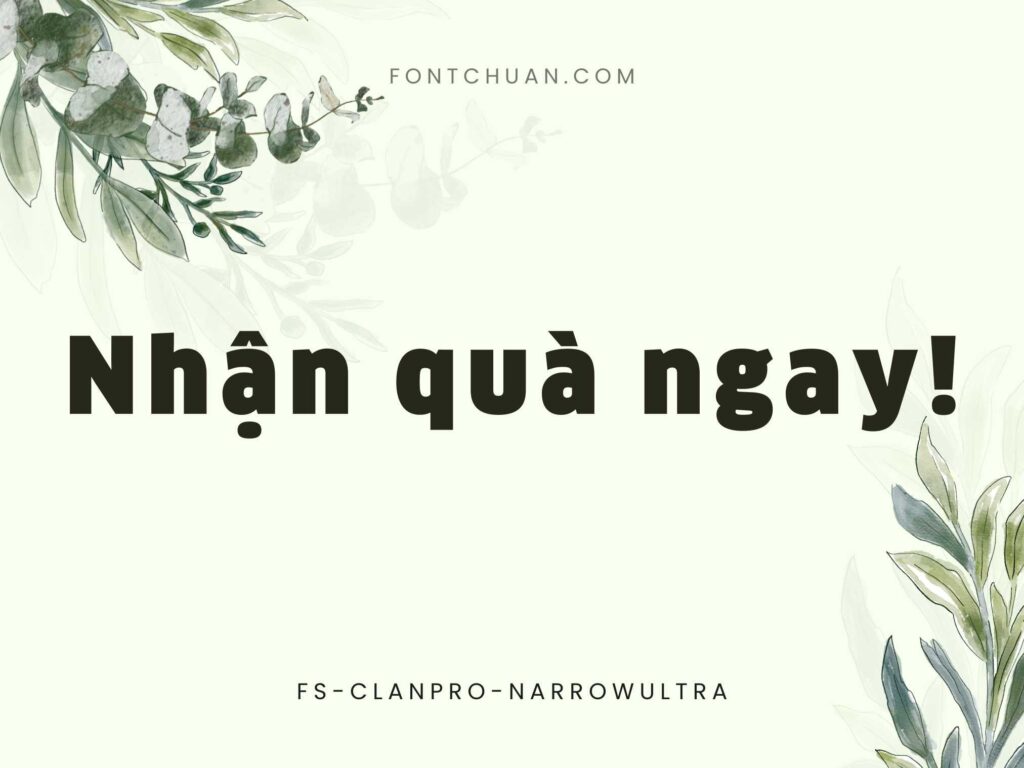
Font FS Clanpro-Narrowultra Việt Hóa
Clan Pro là một họ font sans-serif hiện đại, được thiết kế bởi Łukasz Dziedzic. Với tổng cộng 18 kiểu chữ khác nhau, Clan Pro mang đến sự đa dạng và linh hoạt cho các dự án thiết kế. Phiên bản Narrow Ultra của Clan Pro nổi bật với thiết kế đậm nét và hẹp, tạo cảm giác mạnh mẽ và tinh tế, phù hợp cho các tiêu đề và nội dung cần thu hút sự chú ý. Nhờ sự Việt hóa của Phông Chữ Việt, Clan Pro hỗ trợ đầy đủ các ký tự tiếng Việt, giúp người dùng dễ dàng áp dụng trong các thiết kế đa ngôn ngữ. Thành viên của Font Chuẩn đã sưu tầm và chia sẻ font này nhằm đáp ứng nhu cầu của cộng đồng thiết kế.
Về đặc điểm thiết kế, Clan Pro Narrow Ultra sở hữu các đường nét đậm, gọn gàng và cân đối, mang lại sự hiện đại và chuyên nghiệp cho văn bản. Font bao gồm đầy đủ chữ hoa, chữ thường, số và các ký tự đặc biệt, cùng với hỗ trợ đa ngôn ngữ. Clan Pro Narrow Ultra đặc biệt phù hợp cho các dự án thiết kế như poster, bao bì sản phẩm, thiết kế logo và các ấn phẩm quảng cáo, nơi cần sự nổi bật và ấn tượng mạnh mẽ. Ngoài ra, font này cũng thích hợp cho các sự kiện như lễ hội, sinh nhật, Valentine và Trung thu, mang lại cảm giác ấm áp và gần gũi. Trong lĩnh vực ngành nghề, Clan Pro Narrow Ultra được ứng dụng rộng rãi trong quảng cáo, thiết kế thiệp cưới, giáo dục và công nghệ, góp phần tạo nên sự độc đáo và thu hút cho các sản phẩm và thương hiệu.